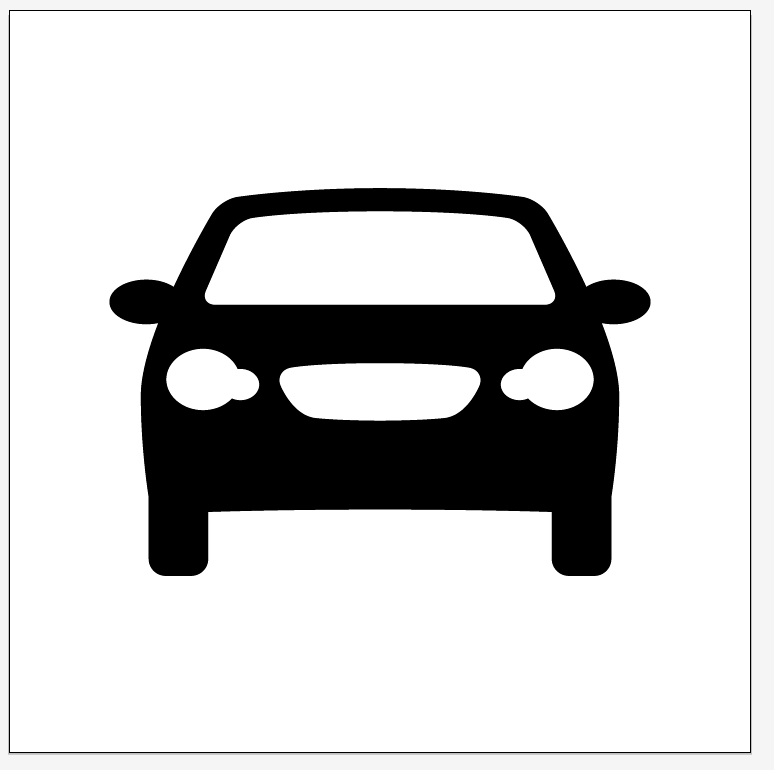
Pictofont in »Wayfinding«
Mit der Wayfinding ist Ralf ja ein -vorsichtig formuliert- höchst respektabler Wurf gelungen. Die im Forum diskutierte Pictosammlung aber als Font in die Familie zu integrieren fänd ich ein wenig schade. Sie als kleines Extrazuckerl den Käufern der Wayfinding dazuzugeben: .o.k.
Sie als (eigenständigen) Freefont zur Verfügung zu stellen ,klar. Aber als integralen Bestandteil der Familie fänd ich letztere damit eher abgewertet.
Fruchtbarer fänd ich einen ganz eigenen Pictofont der erstens formal kongruent läuft mit den Schriften und zweitens auch diese wissenschaftliche Sorgfalt aufweist hinsichtlich dem Bestreben,möglichst maximale Orientierung zu verschaffen.. Die im Moment promotete Pictoammlung scheint mir da vergleichsweise lieblos zusammengewürfelt. Umso bedauernswerter, weil ja die OpenType-Features echte Innovationen enthalten, denen die Gestaltung vieler Pictogramme schlichtweg nicht standhalten.
Wie meinst Du das? Welche Features sind das denn? :interessiert kuck:
Sehr cool, danke Ralf! :-)
Ich frage mich zu Konis Eingangspost Folgendes: Klar, durch die Kombination verschiedener Symbolvorlagen gibt es formale Unterschiede in der Bildsprache der von Dir gesammelten Symbole und das ein oder andere Symbol ist auch durchaus schon ein bisschen angestaubt (Arriving flights, Duschmännchen, …). Die Frage ist aber doch, was Du mit dem Symbolfont bezweckst. Man könnte jetzt natürlich anfangen, die Symbole alle zum einen in ihrer Anmutung zu aktualisieren und zum anderen durch formale Anpassungen an Deine Wayfinding Sans mehr in die von Dir entwickelte Formensprache zu bringen. Das wäre aber – bei der enormen Anzahl von Symbolen – ein ziemlicher Kraftakt. Und wenn Du bei Deiner Absicht bleibst, den Symbolfont kostenlos anzubieten, dann wäre der Aufwand höchstens mit dem Werbeeffekt zu rechtfertigen, der Dir daraus womöglich entstünde.
Ein gangbarer Weg könnte sein, dass Du den – kostenfreien – Piktofont als Forenprojekt ausrufst und jeder der Lust hat, kann alternative Entwürfe für Piktogramme einreichen, die Du dann bei Gefallen gegen die bestehenden Piktogramme austauschst … Das könntest Du dann auch gleich im TJ3 dokumentieren … :-) Und auf typografie.info könnte es dann eine Dokumentation darüber geben, wer welches Zeichen beigesteuert hat …
Und das hieße was?
Die Symbole nach ihrer möglichst raschen und eindeutigen Erkennbarkeit abzuklopfen.
@Kathrin: der Aufwand ist mir auch klar. Aber die
Wayfinding
wurde/wird ja auch nicht so mal im Vorbeigehen aus dem Ärmel geschüttelt. Und weil es eben dieses Aufwandes Bedarf dann kann ich mir auch nicht vorstellen, daß er kostenfrei zu machen ist. So wie die Wayfinding konzipiert ist, schreit sie aber nach einem adäquaten Pictofont. Oder mehreren? Könnt mir nämlich vorstellen die Pictogramme nach Themen geordnet in einzelnen “Schnitten” anzubieten.
Spricht im übrigen natürlich nichts gegen den aktuell diskutierten Pictofont. Ihn in einem Atemzug aber mit der Wayfinding zu nennen, hat diese aber nicht verdient.
Die Symbole nach ihrer möglichst raschen und eindeutigen und Erkennbarkeit abzuklopfen.
Okay, das wäre natürlich ein Unterfangen, dass viele Jahre und viel Geld verschlingen würde.
Es gibt ja auch Leute, die sich damit beschäftigen:
Aber sowas sprengt natürlich alles den Rahmen meines »Bonusfonts«.
Ich bin übrigens nicht mal der Meinung, dass für solche Symbole eine allgemeine Erkennbarkeit »gemessen« werden kann. Auch da gilt: Wir lesen am besten, was wir am meisten lesen. Die am besten erkennbaren Symbole sind schlicht die, die wir am häufigsten gesehen haben, selbst wenn es formal vermeintliche bessere Symbole gäbe, die entweder klarer sind, oder realitätsnäher, oder abstrahierter oder was auch immer. Insofern sind solche Symbole einfach unglaublich schwer testbar, weil die persönliche Erfahrung und der Kulturkreis einfach so viel wichtiger sind als die Gestaltung des Symbols selber.
Gilt aber für Schriften genauso!
Könnt mir aber schon vorstellen, daß allein mit Deinem bisherigen Erfahrungsschatz, Du schon brauchbarere Ergebnisse zu Stande bringen könntest.
Viele Formen der AIGA - Symbole sind einfach inzwischen soweit überholt, daß sie nur noch erschwert (im Sinne von verlangsamt) “lesbar” sind. Allein die Fahrzeugsymbole: Der Geländewagen ist von normalen PKW doch kaum unterscheidbar. Ein bisschen windschnittigkeit in den PKW gebracht (vergleichbar dem Zug) und schon ist viel gewonnen.
Der Badewanne gönnt man da zwei Füßchen und einen nostalgischen Rand. Ausgerechnet eine Form die nun wirklich simpel zu absrtrahieren ist wird mit Details aufgeladen.
Trotzdem seis nochmal wiederholt: mich stört die Sammlung als Bonusfont so überhaupt nicht. Wird dem Anspruch der Wayfining aber halt so überhaupt nicht gerecht. Und in die technische Umsetzung ist ja auch schon einiges an Arbeit geflossen. Diese fänd ich bei weitem sinnvoller investiert, ginge man auch nochmal an die Überarbeitung der Gestaltung.
Aber gut lesen lässt es sich allemal ... Am problematischsten sind die Erdnuss-Scheinwerfer ...
Den Abstrhierungsgrad noch weitergetrieben und schon ist es eben wirkungsvoller als dieses inzwischen plump wirkende AIGA-Pendant
Dacht ich mir' date=' dass das in Europa (falsch) als Mercedes erkannt wird. ;-)[/quote']
Ich wurde genasführt ...!
Zurück zum Thema: Ralf, Dein Autopiktogramm ist wirklich schöner als das AIGA-Symbol. Aber Du hast vermutlich keine Lust, die Überarbeitung Deiner Piktosammlung flächendeckend anzugehen, oder?